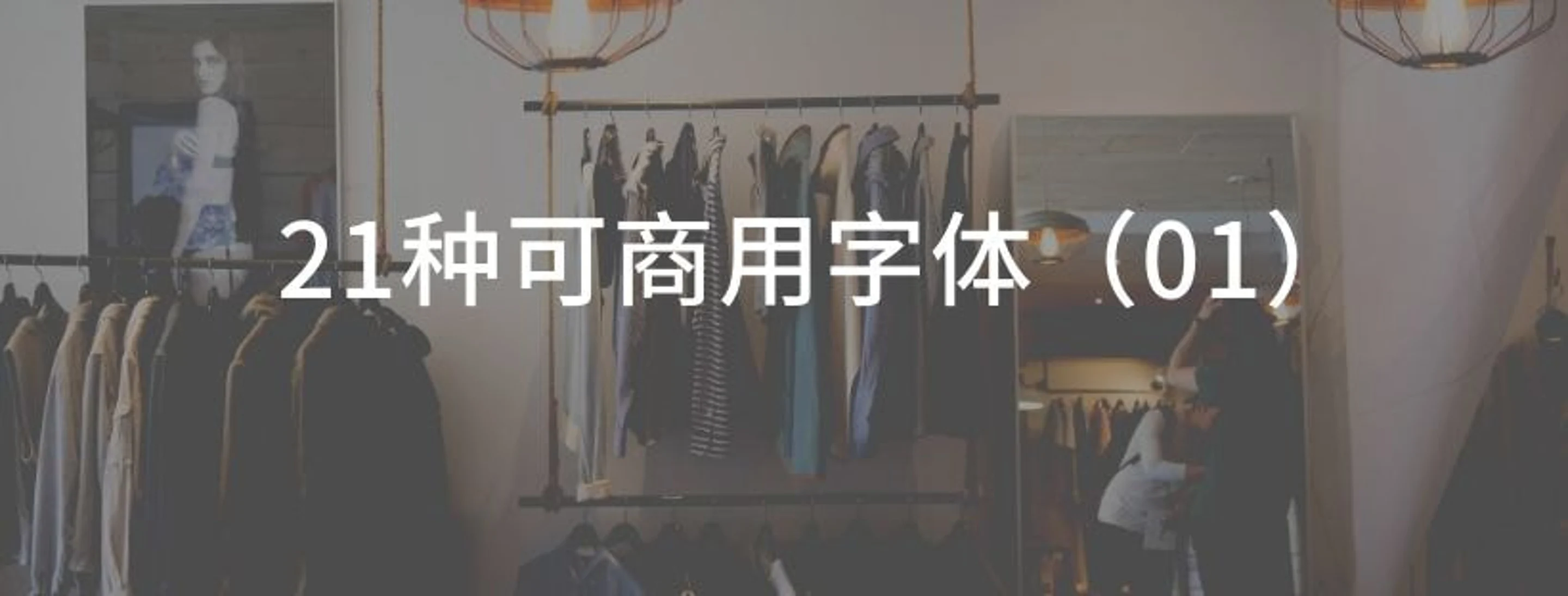
这次我们来聊聊有哪些是可商用字体,如何发掘他们的用武之地,并为其搭配不同应用场景和风格。
「落其实者思其树,饮其流者怀其源」,思源字体正是暗含着设计师饮水思源的良苦用心。
“在数字时代,为了让字体能够更好地帮助人们获取信息及相互交流沟通,更好地适应到不同的载体,并能在不同区域之间的信息沟通中发挥更好的作用,我们设计出了思源黑体。”
——参与字体设计的西塚涼子女士
它是由是Adobe与Google所领导开发的开源字体家族,无衬线黑体。思源黑体的设计初衷,是支持各类载体(特别是电子屏)的传播与可读,故而笔画宽度平直,粗细变化极小。思源黑体较为常见如正式的工作场景、学术场景抑或是高端大气的发布会场景,偶尔给表情包配个字体,也是挺适用的呢!
思源宋体开发用时接近3年,字体特点是中宫更大、重心更低,而且它增加了对数字设备显示的优化,能同时胜任「印刷」和「显示」的一款「泛用型」的字体。在对字体竖版的显示上,思源宋体具有天然的“竖式排版”的优势。因此,思源字体不仅具有数字化给予字体的现代感,它同样能驾驭很多古典传统化的使用场景,
方正黑体的笔画两端留有喇叭口,撇、捺、钩笔画的粗细变化较大,中宫比较紧凑。其字重适中、字形风格中性朴实,适合在书籍、杂志,也适合广告印刷媒介屏幕阅读,是一款非常经典的正文黑体。
方正楷体与“华文楷体”一脉相传,有着较强的历史痕迹,在教科书中最为常见。
方正楷体的结构秀丽匀称,笔画圆润柔和,横竖笔画的粗细变化不大。这款字体被大量应用于报纸、杂志和书籍中的正文。它古典、简洁、端庄,适合商务手册和正式文件印发。
方正仿宋源于铅字时代,制作者仿宋版书中的瘦细字体而制成,因此这款字体字身略窄,笔画瘦硬,横竖笔画等粗,起笔处有斜势棱角,折笔处棱角分明,整体字形挺拔俊秀,给人以悦目之感。因清晰美观,容易辨认,长期被用于工程图纸文字和书刊中的引文。
方正书宋最初的设计就是专门针对正文排版。方正书宋的字形端正清秀,中宫适度。凭着清晰爽目、久读不易疲劳、印刷适性好的优点,长期被作为杂志和书籍的正文首选字体,所以也是一款非常经典的正文宋体。